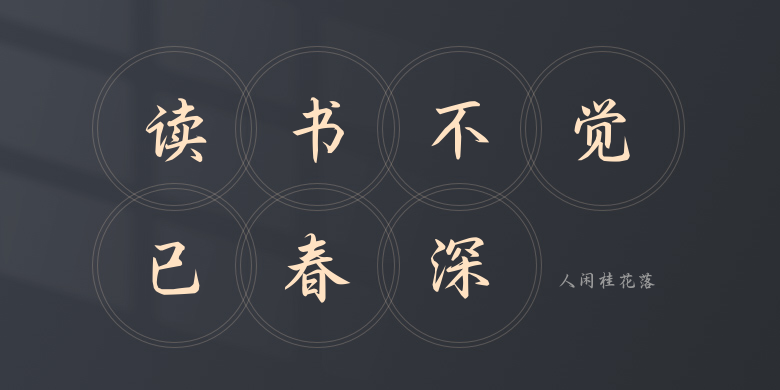
人闲桂花落
人闲桂花落,这款字体结构工整、笔画清晰,兼顾美观与易读性,适用于标题、正文、海报、包装、LOGO 等多种场景。字形优雅稳定,风格百搭耐看,适配日常排版与创意设计,让文字呈现更舒适、更具质感。人闲桂花落一笔一画,皆是细节,以均衡的比例、流畅的线条打造舒适视觉体验,字形端正大气,风格简约现代。无论是商业设计、品牌宣传还是日常排版,都能轻松驾驭,让文字更有格调与力量。人闲桂花落字体下载。